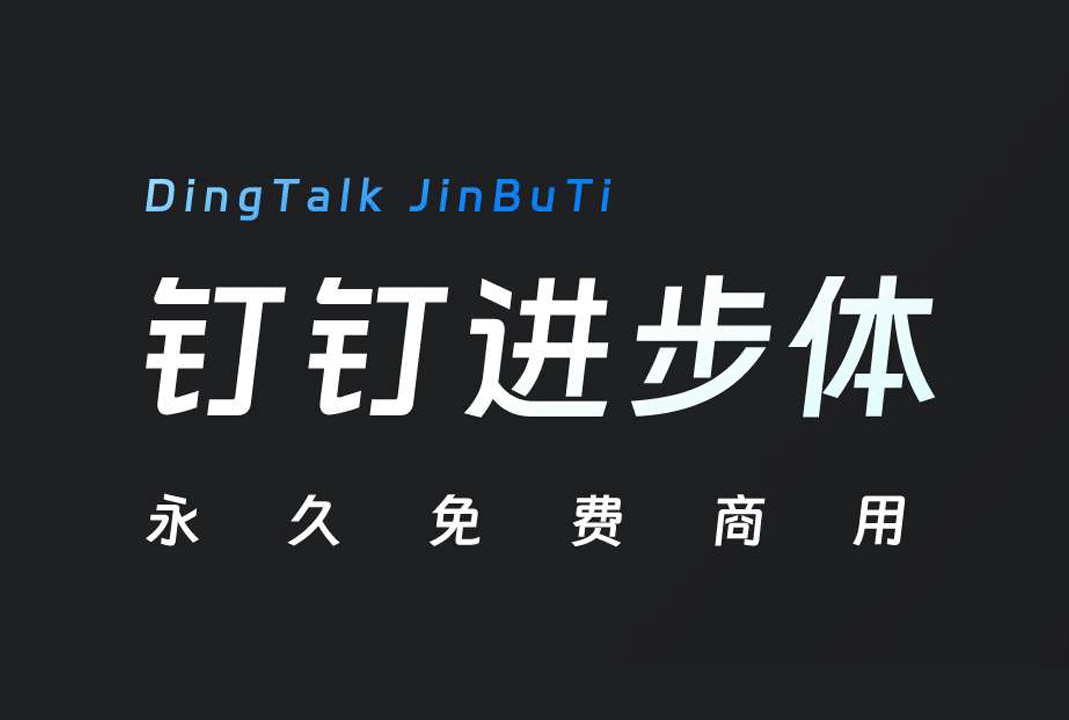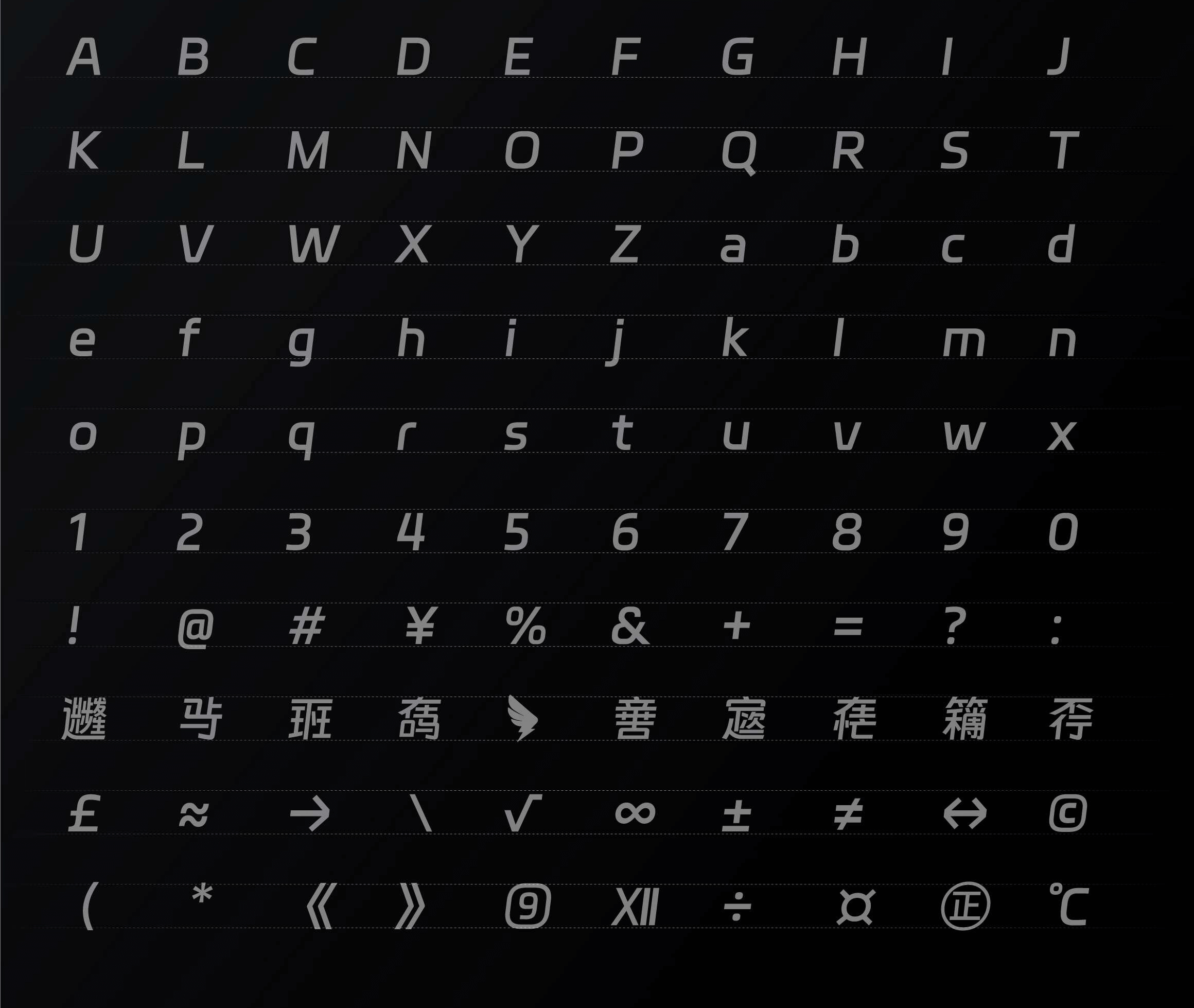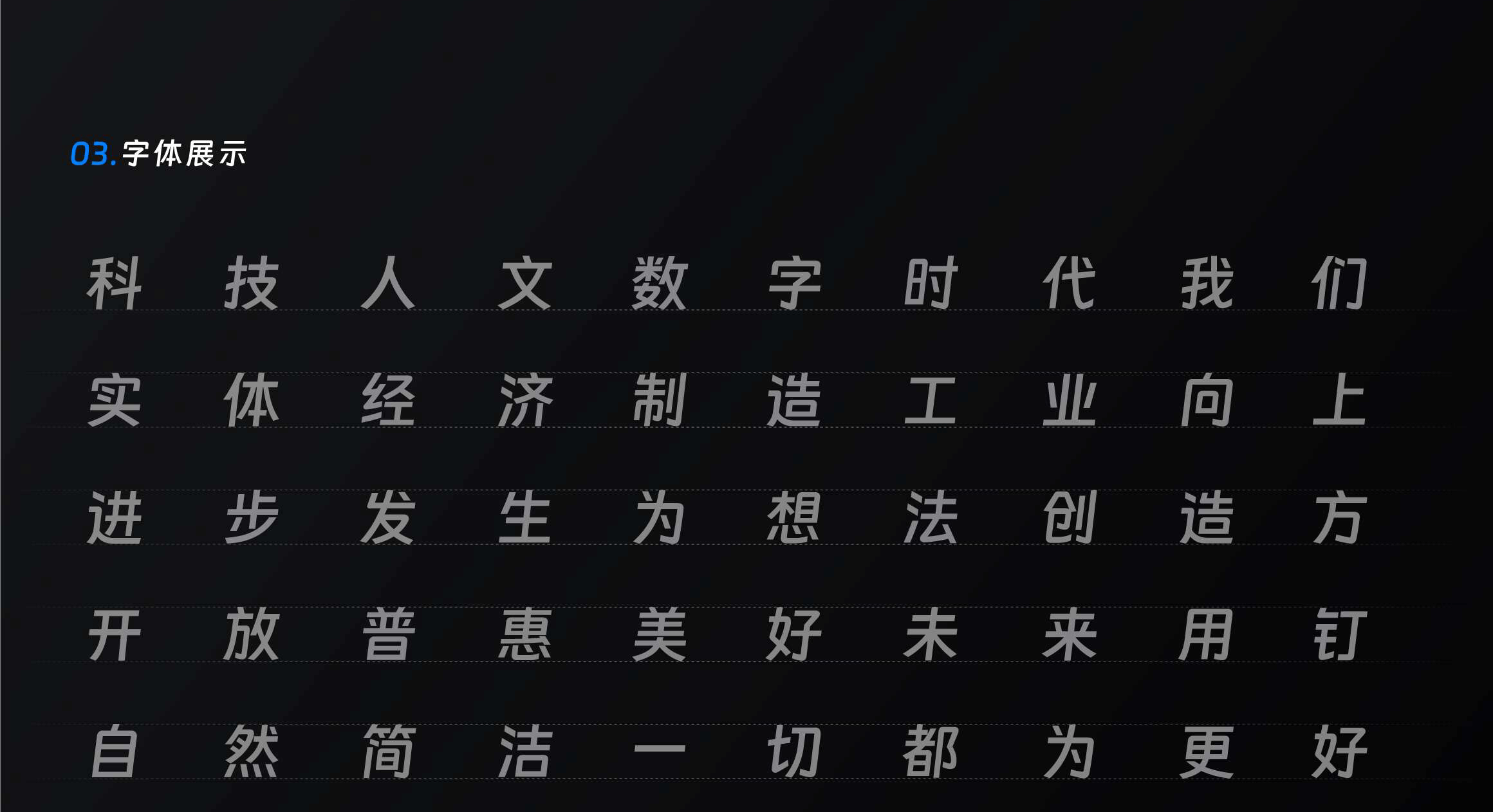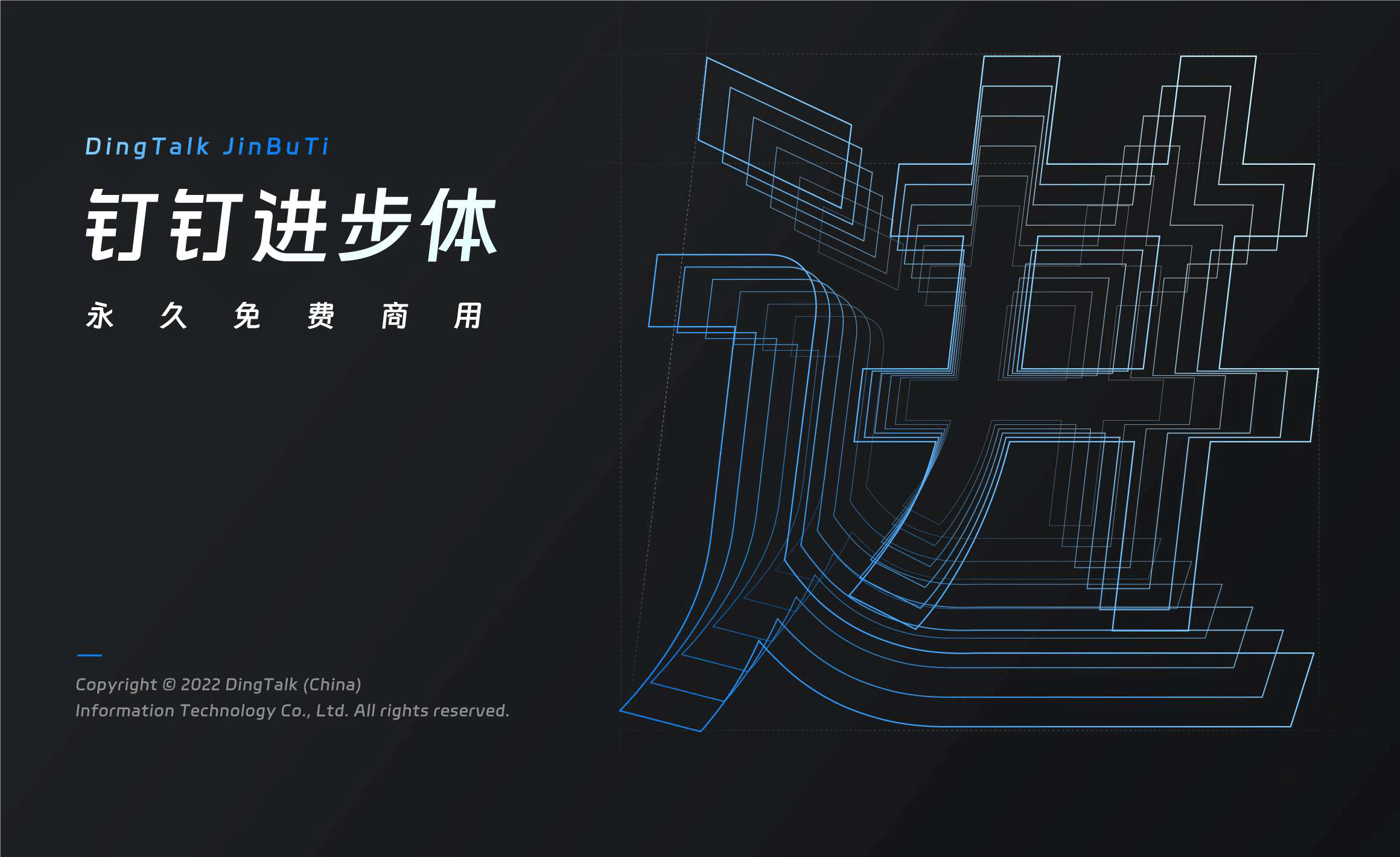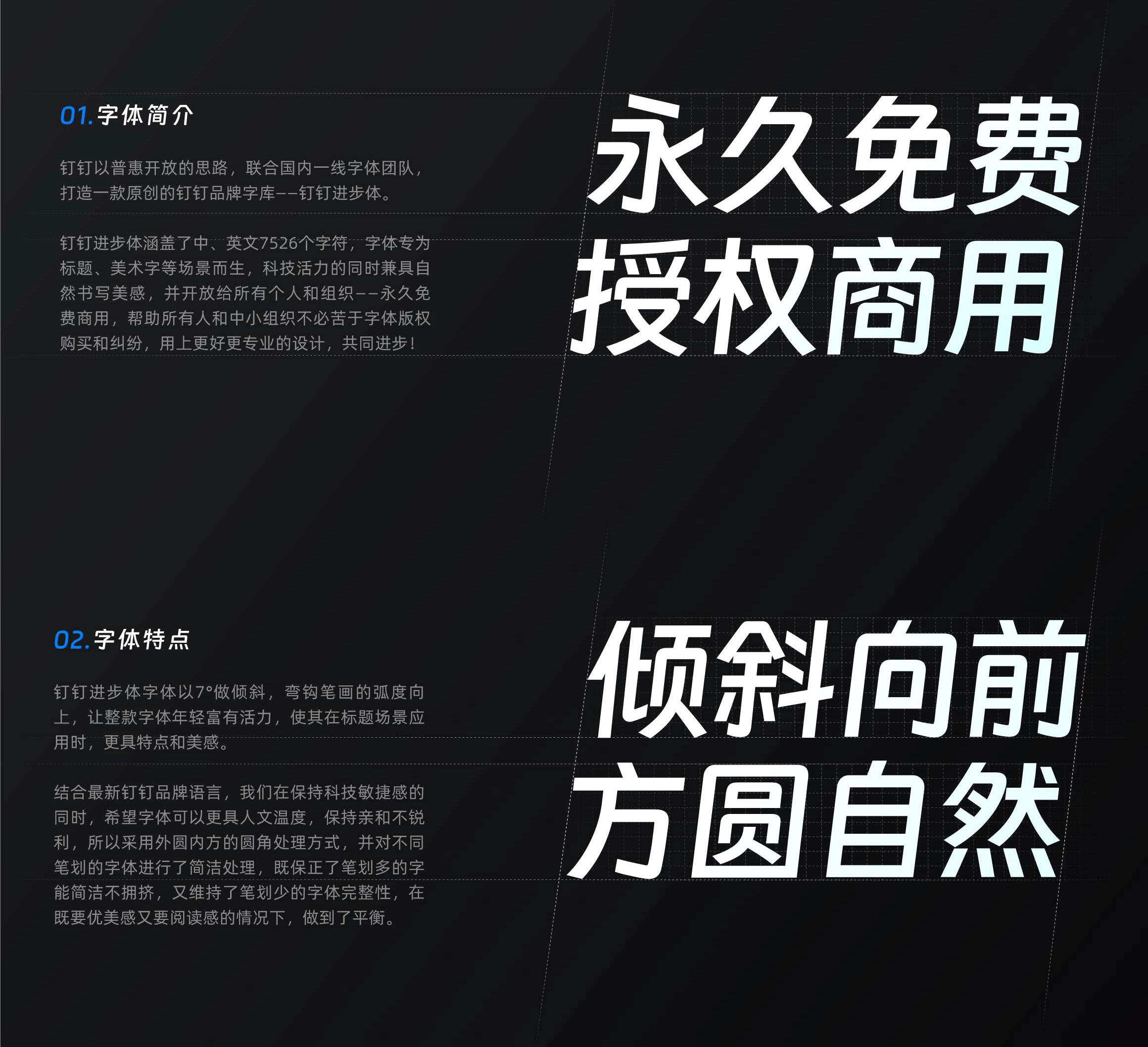
钉钉进步体是阿里钉钉发布的一款中文可免费商用字库,该字体以普惠开放的思路,联合国内一线字体团队共同打造。
钉钉进步体涵盖了中、英文 7526 个字符,字体年轻富有活力,字体专为标题、美术字等场景而生,科技活力的同时兼具自然书写美感,并开放给所有个人和组织永久免费商用,帮助所有人和中小组织不必苦于字体版权购买和纠纷。